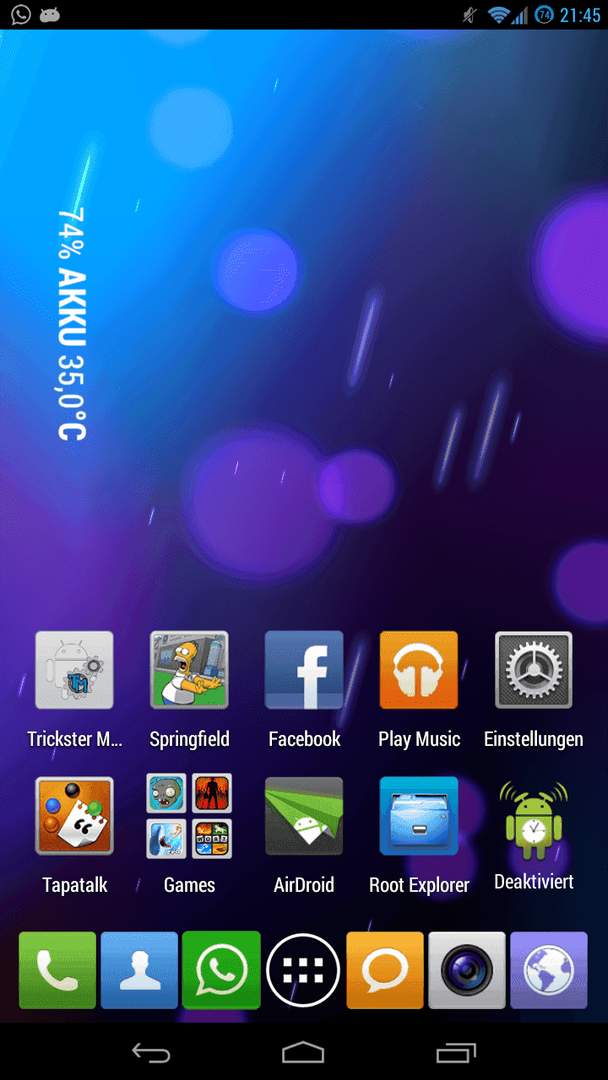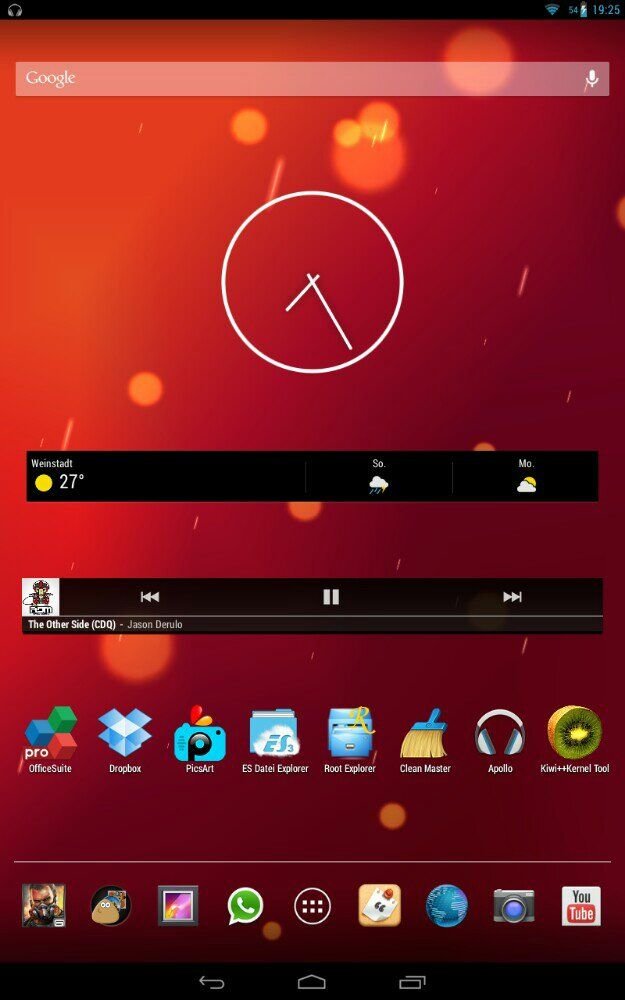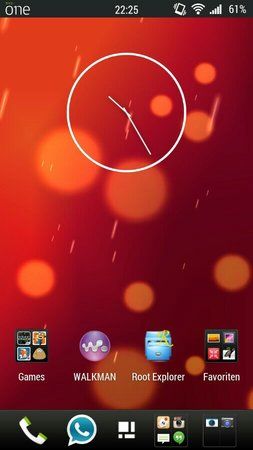
Android 4.3: Neue Schriftart
Ich find sie hammer,sie sieht einfach super aus :)
Habs gerade geflasht. Obwohl die Buchstaben schmäler sind, kann mans perfekt lesen. :)
Ich mag sie,besonders weil sie sehr an die Schrift vom HTC One erinnert :) Und ich liebe das One einfach,also hab ich immer einen Teil vom One bei mir :D
An meinem One X sieht es auch sehr gut aus,klasse Google :p